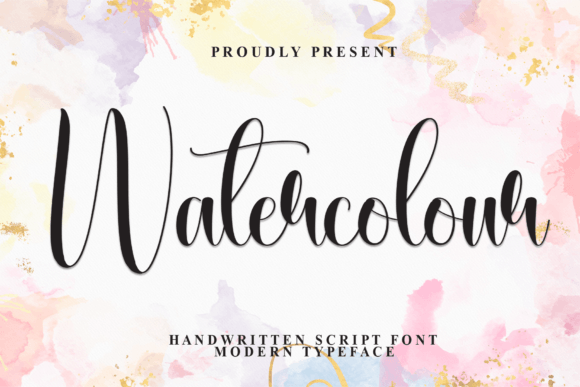
Watercolour
Watercolourのような高品質の素材をお探しの場合、このプレミアムパッケージはクリエイティブなプロジェクトに素晴らしい選択です。
POD(オンデマンド印刷)製品、結婚式の招待状、またはソーシャルメディアのグラフィックを作成している場合でも、Watercolourは理想的です。